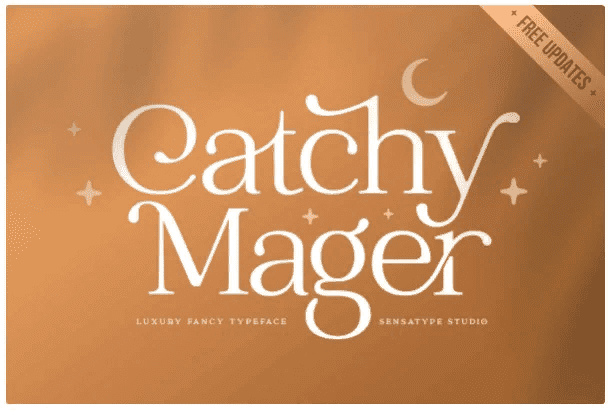
Название: Catchy Mager Font (2021)
Catchy Mager (бывший John Mayer) - это уникальный и очень элегантный шрифт для дизайна бренда и логотипа.
Исходя из нашего опыта работы в качестве графического дизайнера, который работает для многих компаний, нас часто просят разработать логотип в уникальном стиле, но с элегантной формой. Поэтому мы пытаемся провести мозговой штурм и создаем этот шрифт, чтобы воплотить идею в жизнь. Он идеально подходит для БРЭНДИНГА и ДИЗАЙНА ЛОГОТИПА. С помощью этого шрифта вы получите стильные, элегантные и, безусловно, уникальные логотипы.